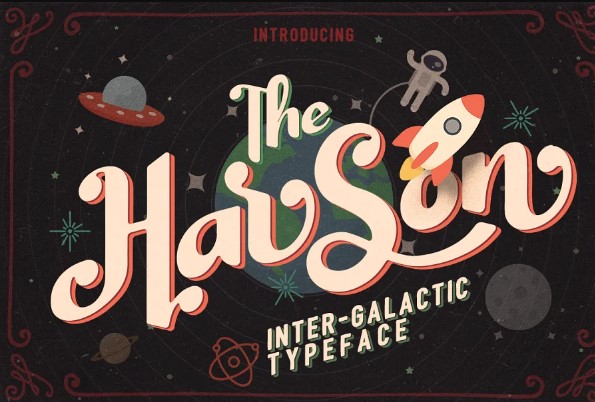
[Creativemarket] Harson Soft Font
Этот шрифт был вдохновлен старинными журналами и старыми названиями фильмов.
Harson
поставляется с заглавными и строчными буквами, цифрами, знаками препинания, валютными символами и множеством вариаций на каждом символе, включая чередующиеся символы открытого типа, а также общие лигатуры. Также поддерживается Contextual Alternate, так что альтернативные символы будут автоматически генерироваться на каждом последнем символе при наборе слова. Harson идеально подходит для использования в качестве логотипа, бланка, плаката, дизайна одежды, этикетки и т.д.